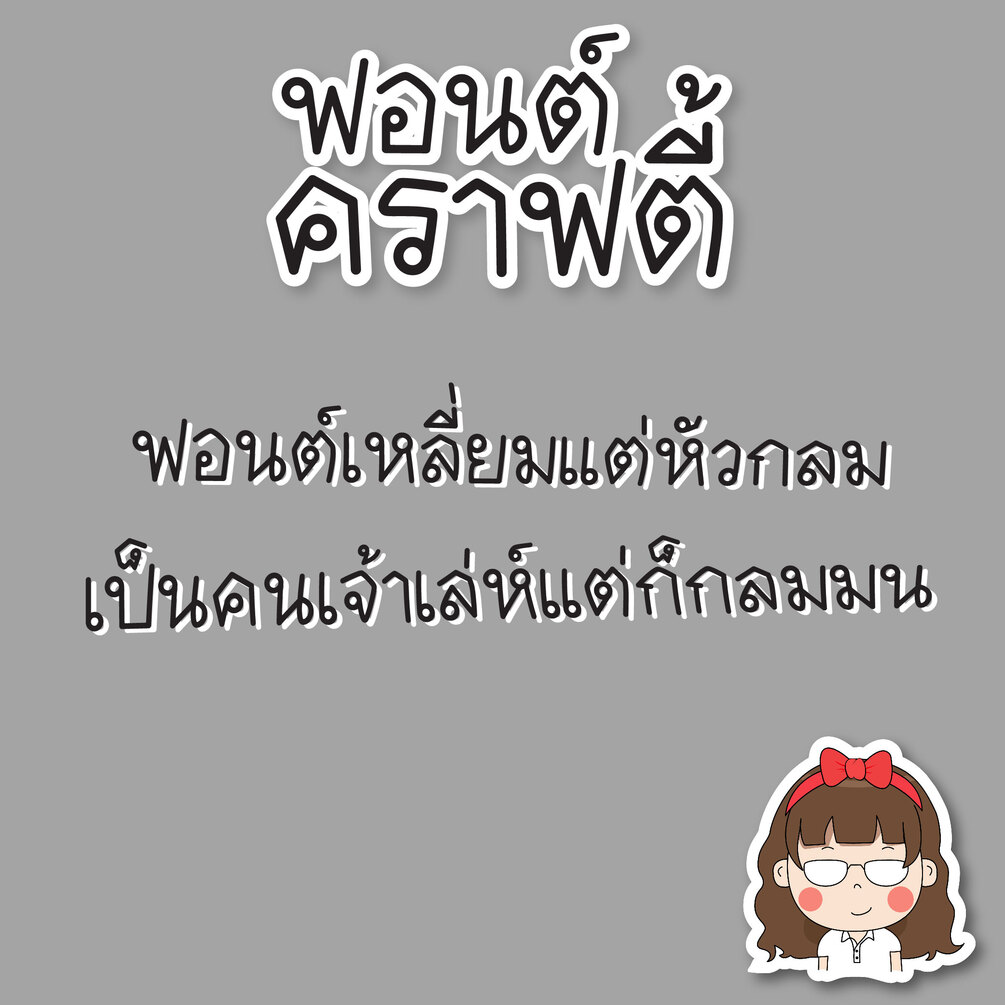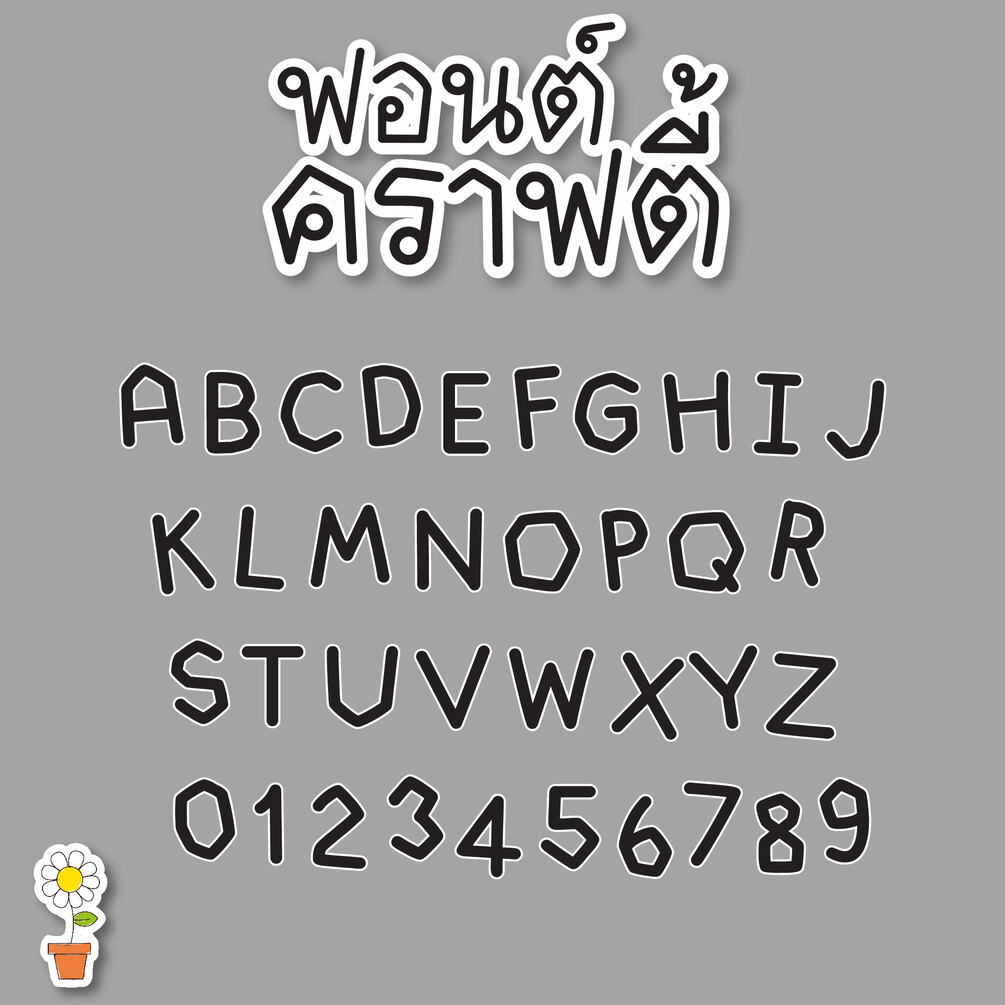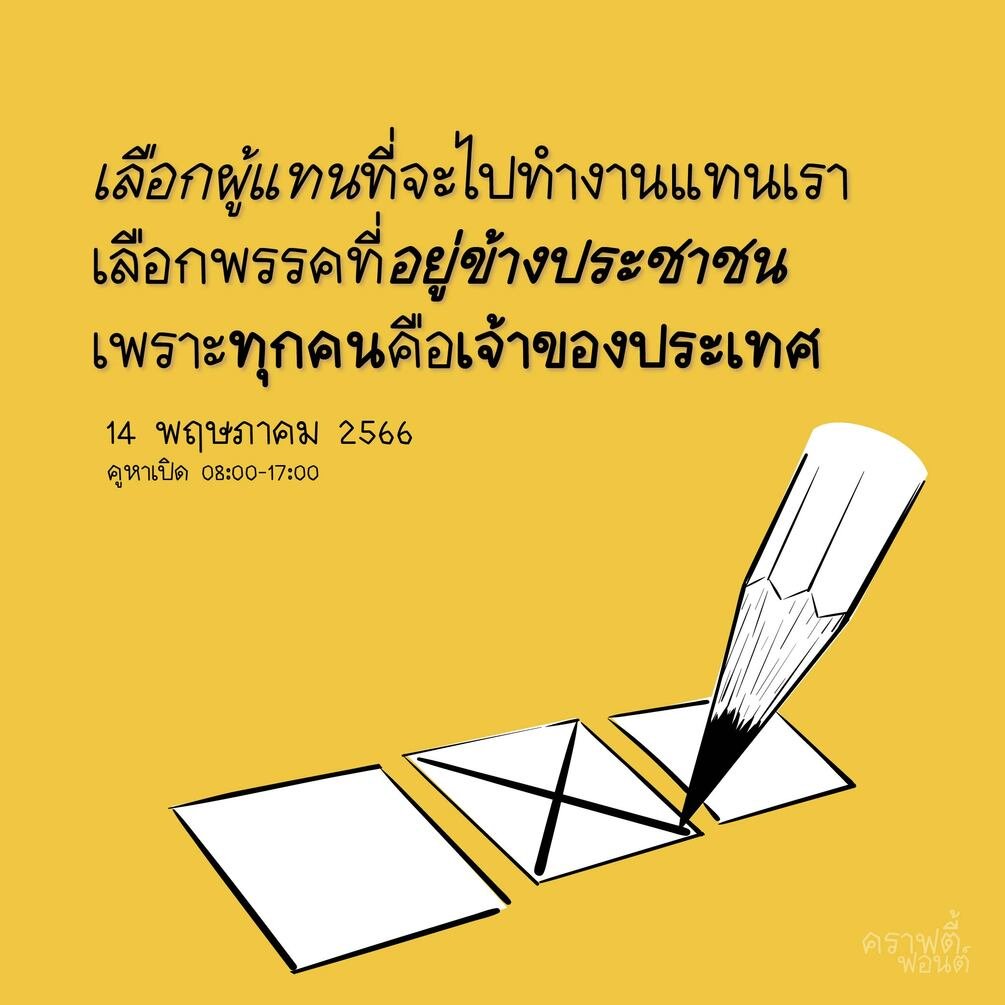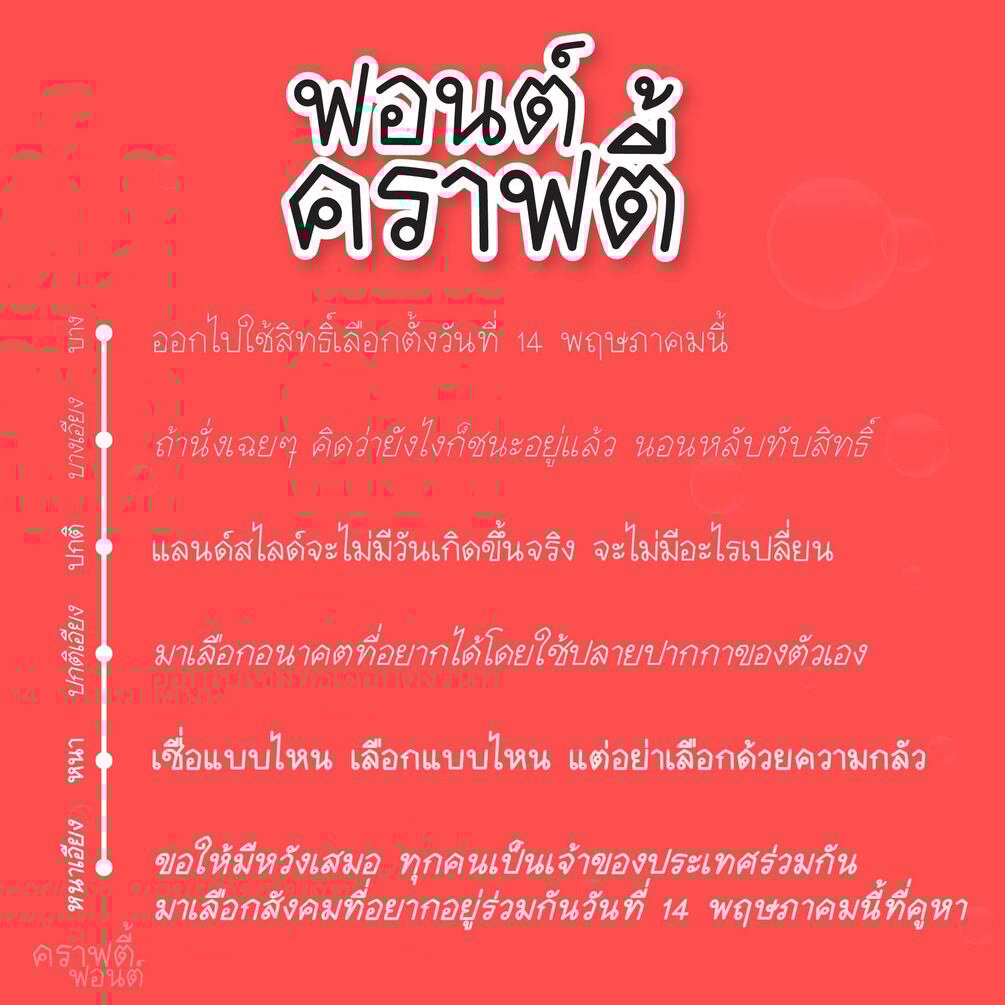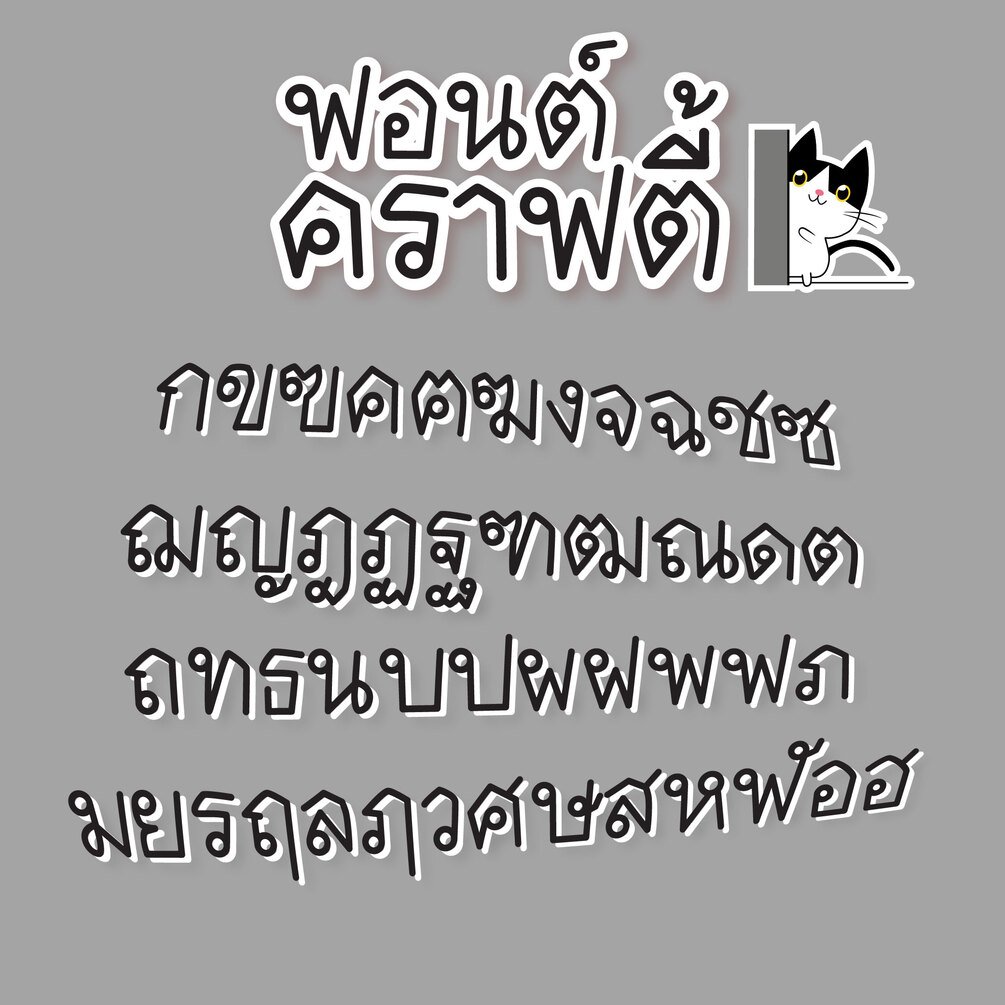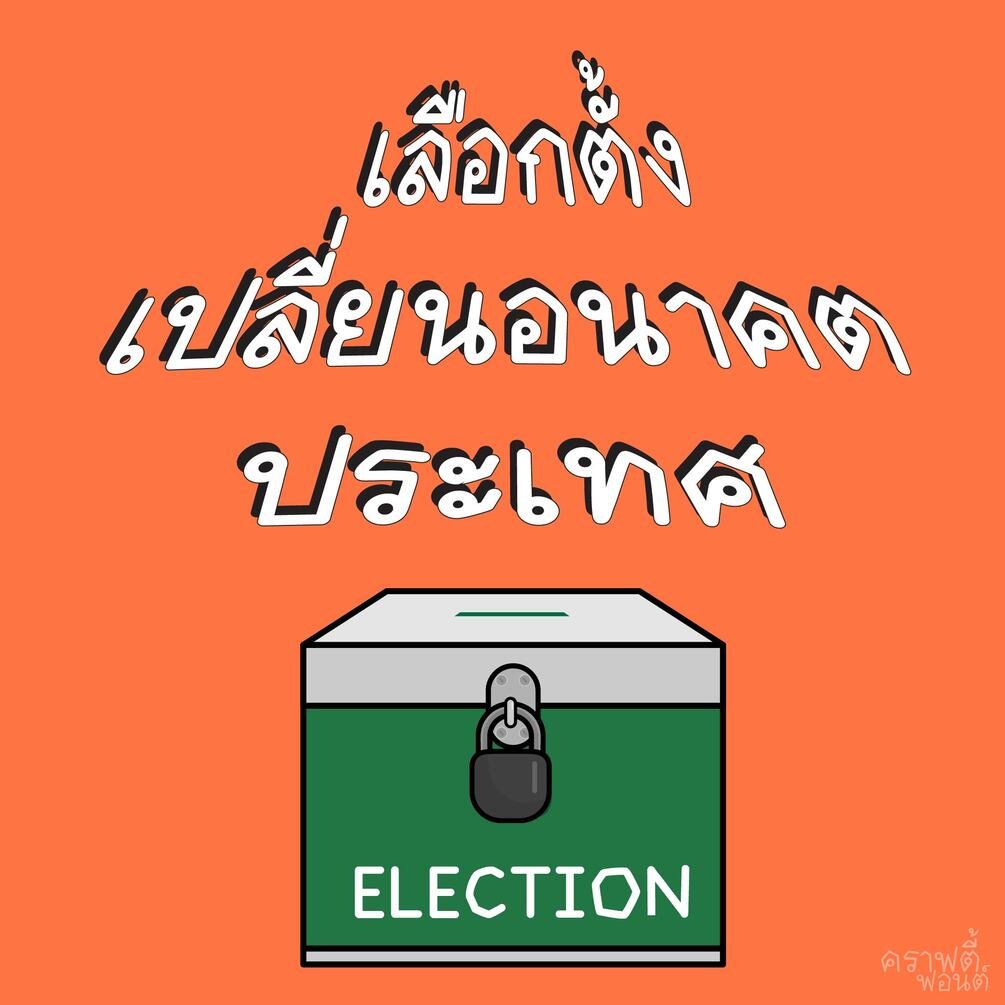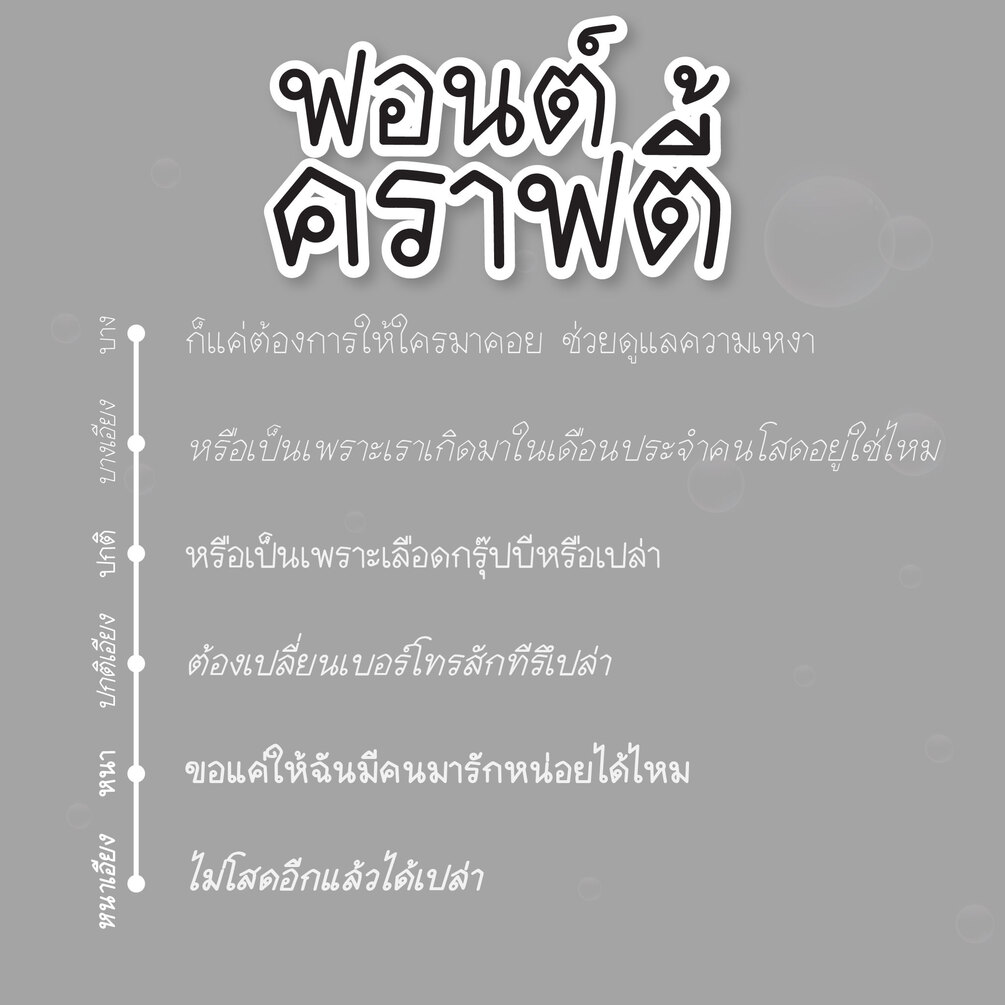
crafty font (คราฟตี้ฟอนต์)
ฟอนต์คราฟตี้ (Crafty Font) ถูกดีไซน์ให้เป็นตัวเหลี่ยมหัวกลม เจ้าเล่ห์นิดๆ แต่โดยรวมน่ารัก! 🥰 แฟมิลี่เซ็ตนี้มีทั้งหมด 6 น้ำหนักด้วยกัน (ตัวปกติ ตัวเอียง ตัวหนา ตัวหนาเอียง ตัวบาง และตัวบางเอียง) ฝากไว้ในอ้อมอกอ้อมใจพี่จ๋าด้วยนะจ๊ะ 💖